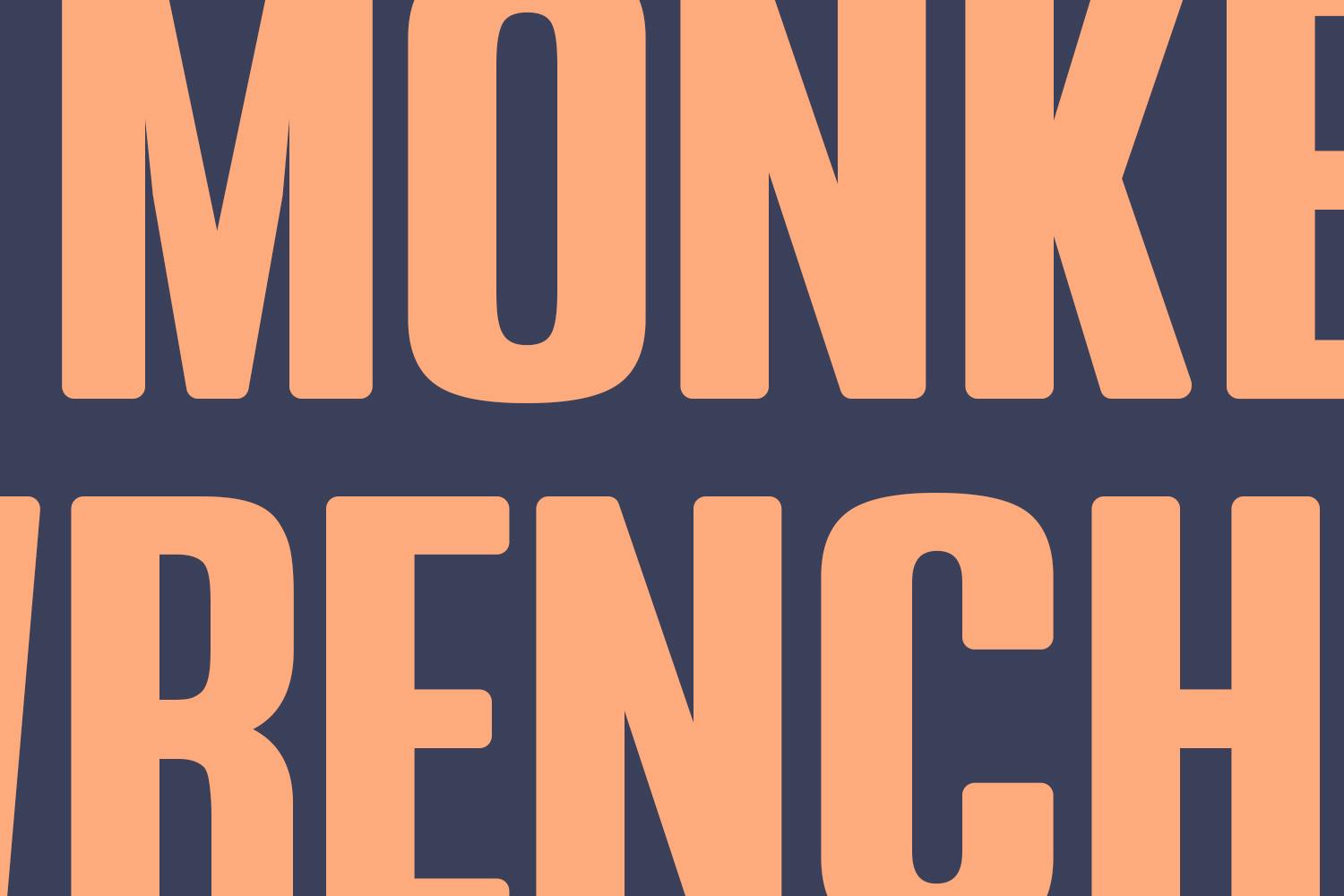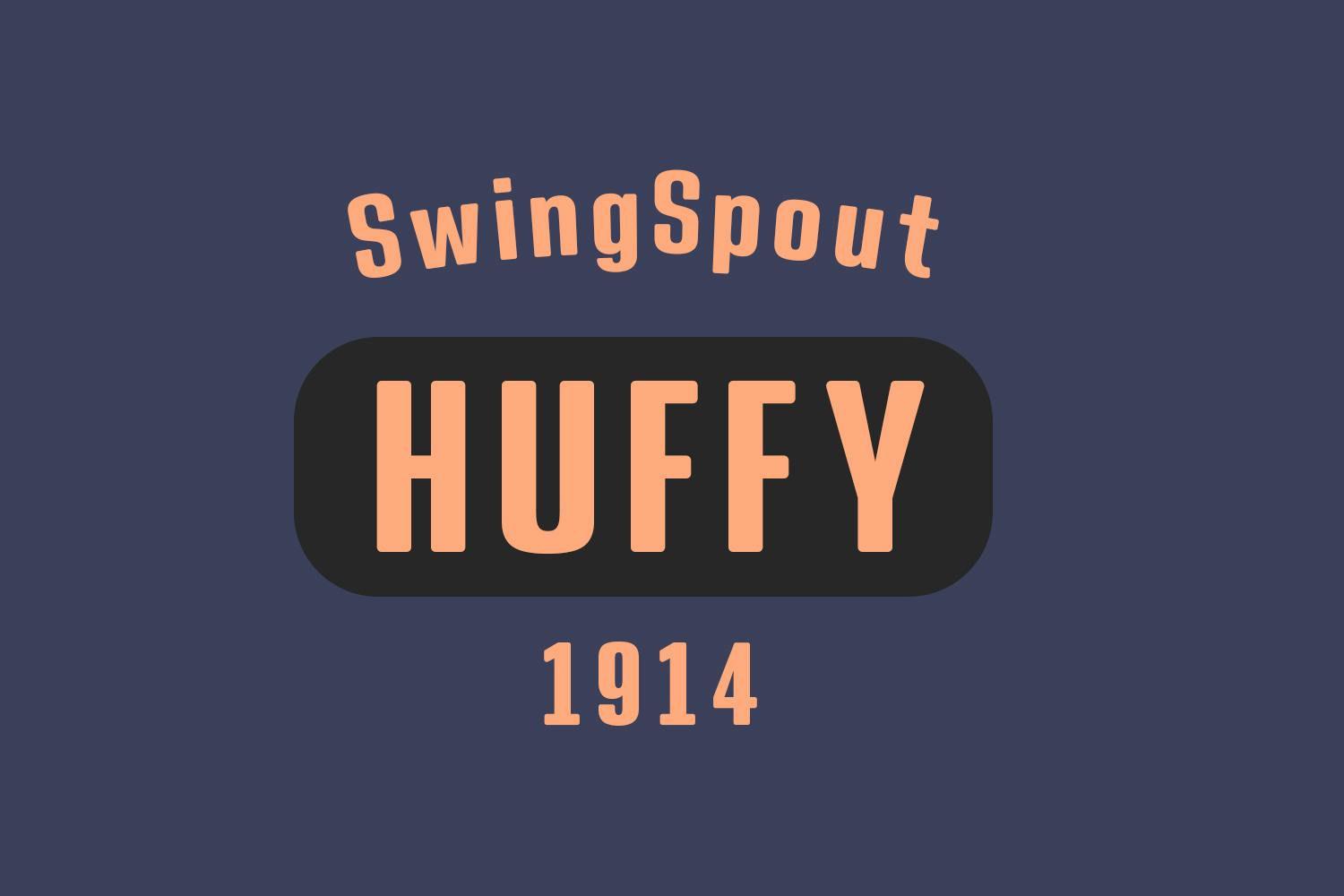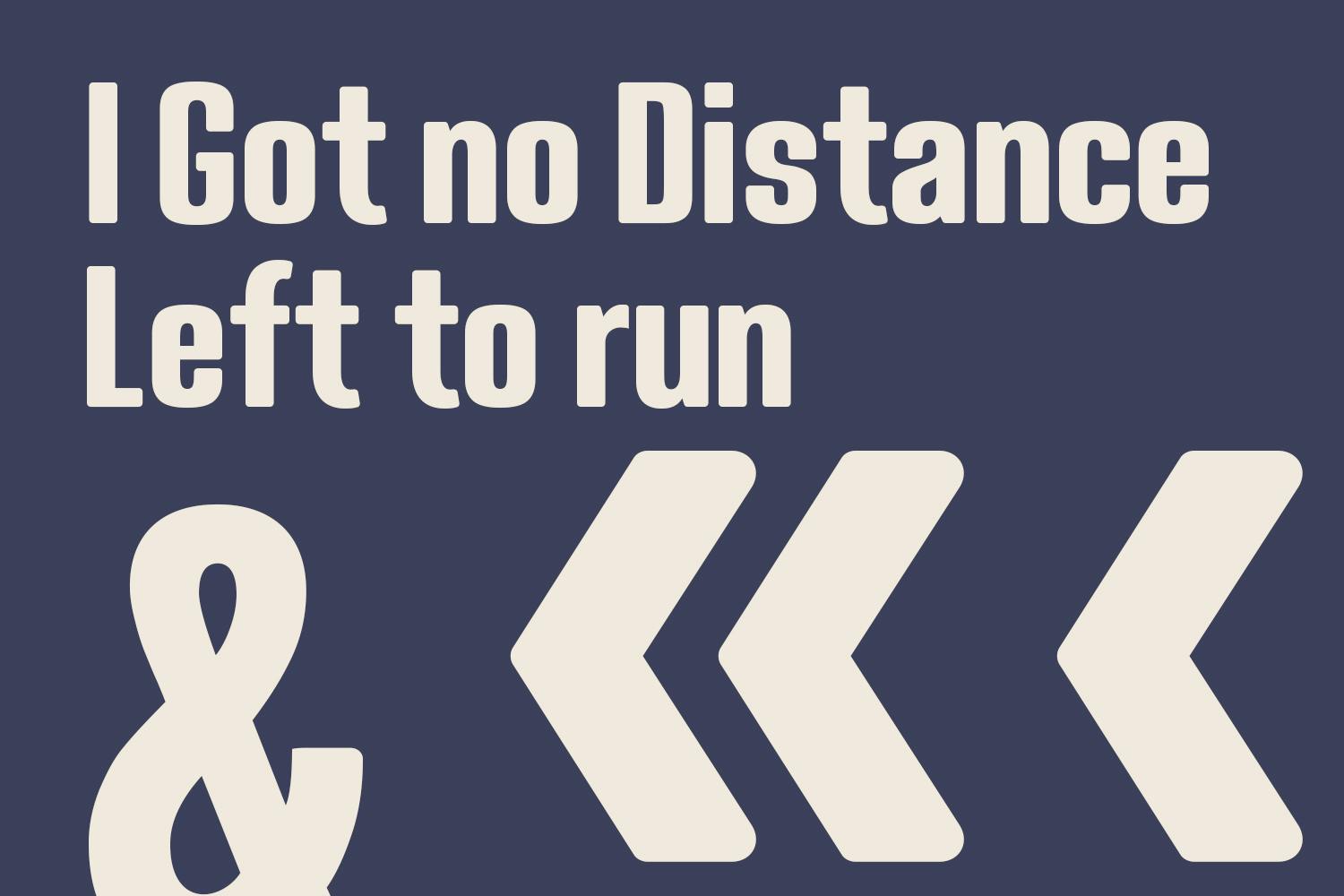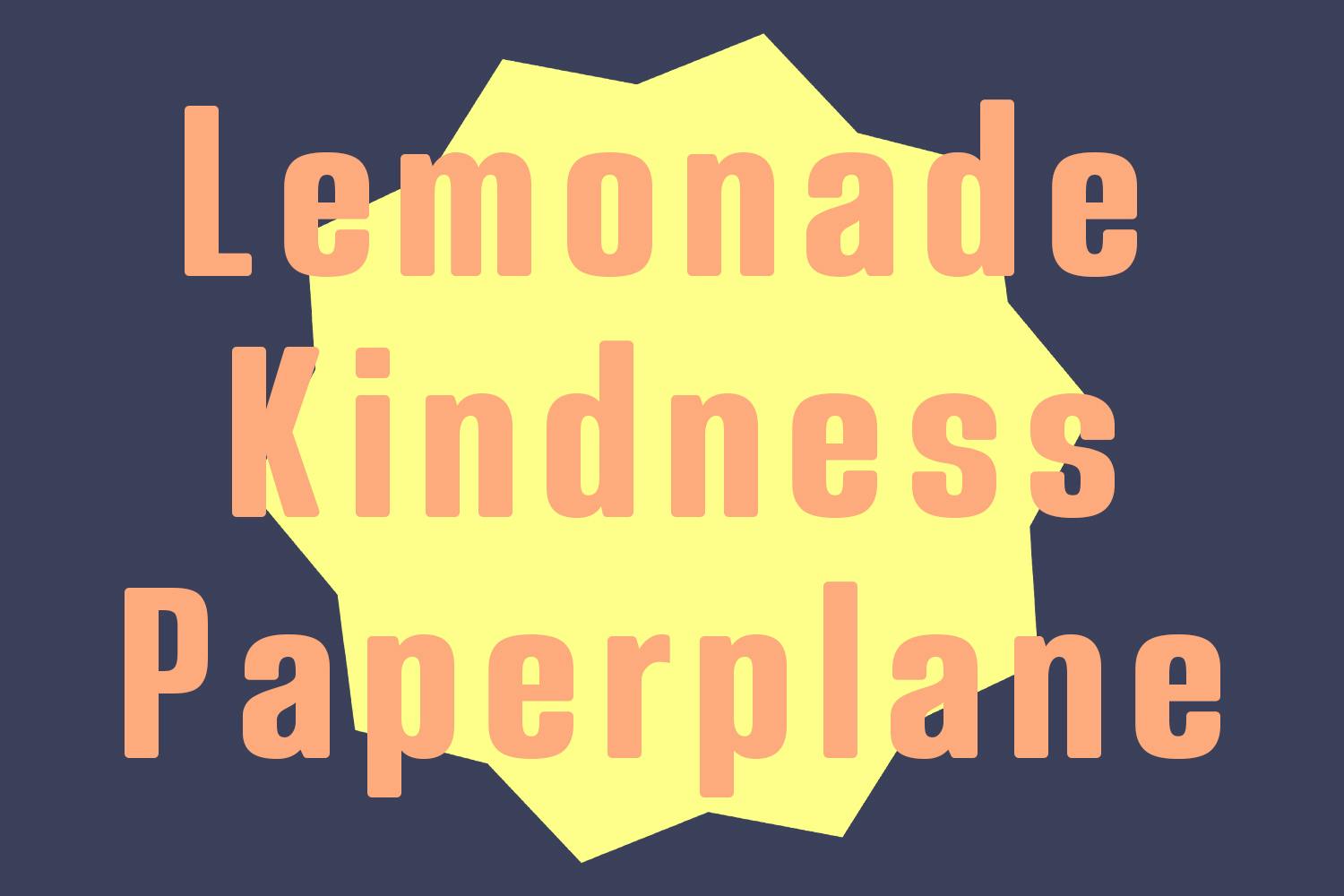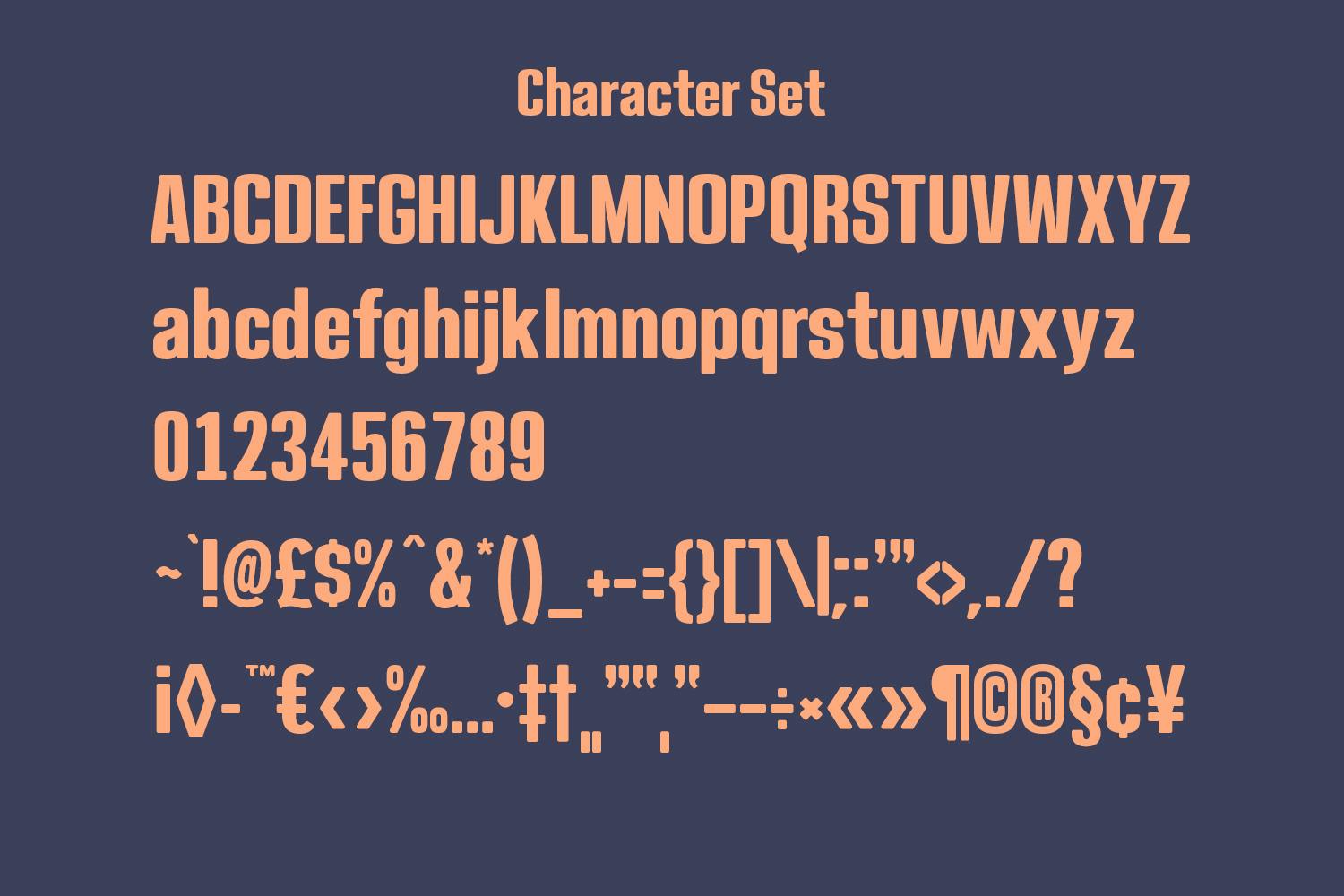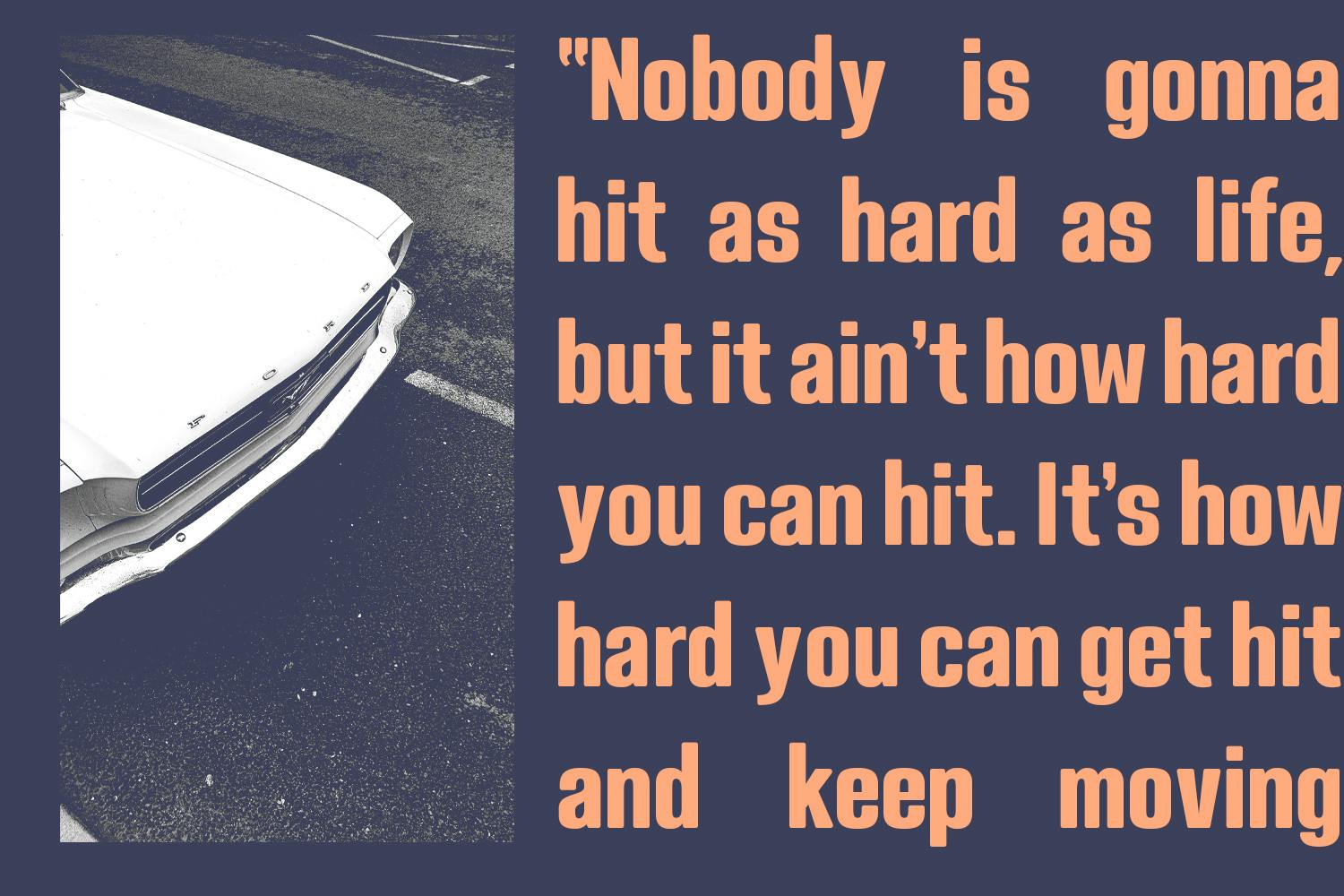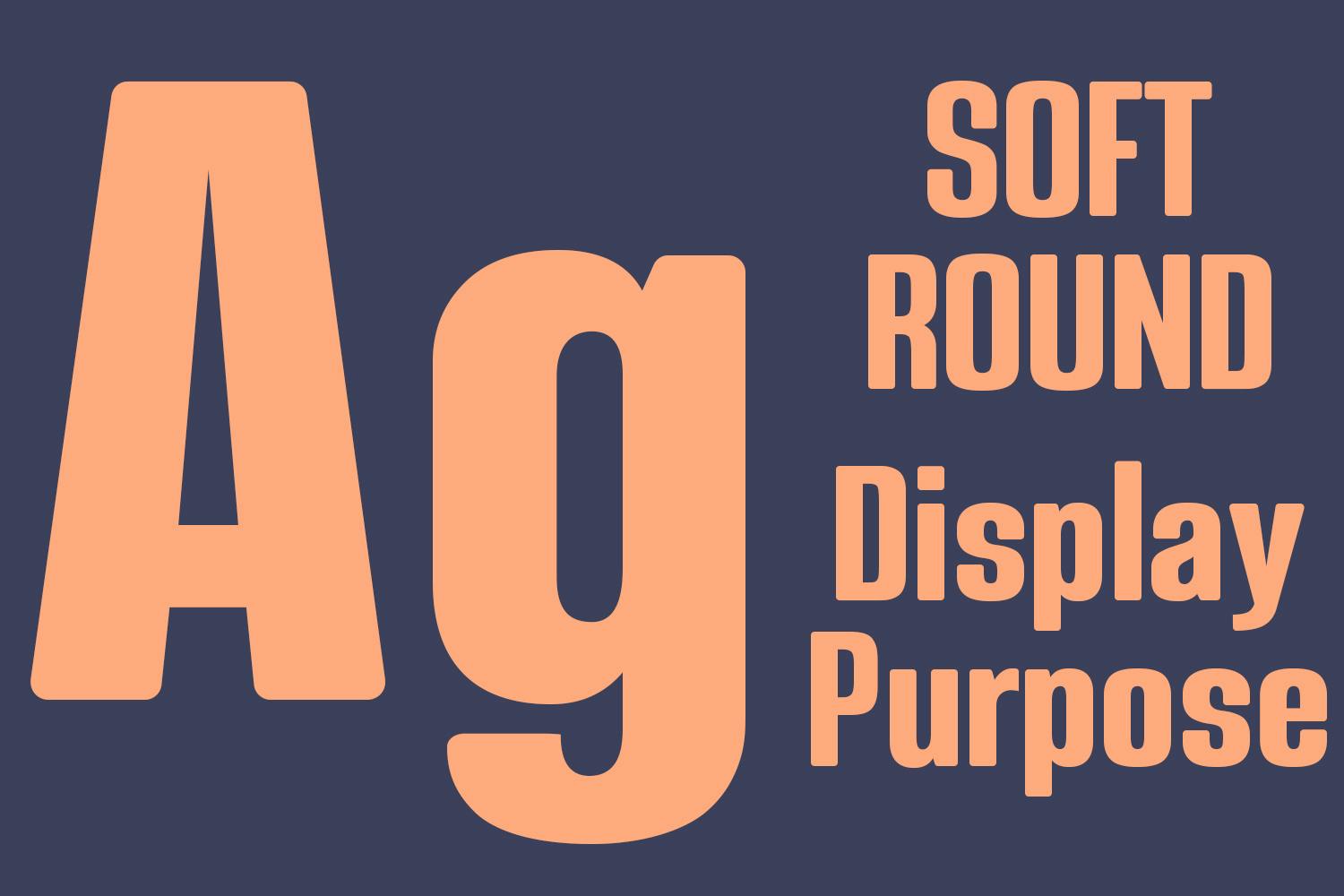
فونت دیفویلز یک فونت کلاسیک بدون سریف است. با ضخامت متوسط، شخصیت جذاب و کمی ترکیب و جایگزینهای خاص، این فونت به شما امکان میدهد تا کارهای خلاقانهتری را ارائه دهید. فونت دیفویلز از بیش از 100 زبان مختلف پشتیبانی میکند. این فونت برای طراحی لوگو، شبکههای اجتماعی، عناوین فیلمها، عناوین کتابها، متنهای کوتاه و حتی نامههای طولانی مناسب است و به عنوان فونت ثانویه با فونتهای اسکریپت یا سریف نیز عالی عمل میکند. با فونت دیفویلز، کارهای شگفتانگیزی خلق کنید.